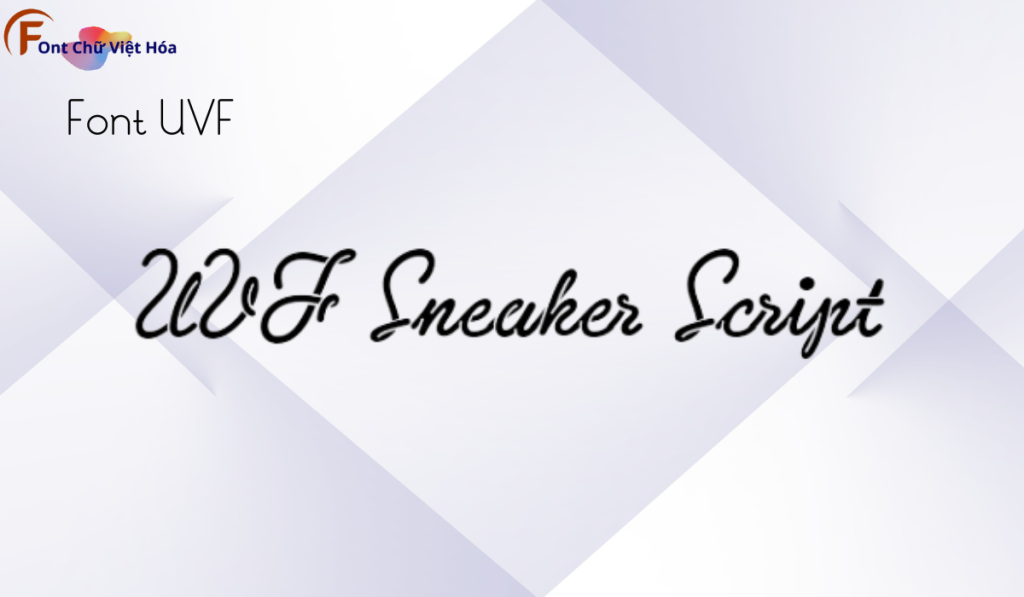
Font UVF Sneaker Script Việt Hóa
Bộ Font: UVF
Kiểu chữ: Script
UVF Sneaker Script Việt Hóa, thuộc bộ font UVF, mang phong cách chữ thảo với các đường nét mềm mại và tinh tế. Font này được thiết kế nhằm mục tiêu tạo ra sự thanh lịch và dễ đọc, đặc biệt phù hợp cho các thiết kế như thiệp mời, poster, và logo. Đặc điểm hình dạng của UVF Sneaker Script là các đường nét rõ ràng và tỷ lệ chữ cân đối, giúp tạo ấn tượng thị giác mạnh mẽ và sự thanh lịch trong từng chi tiết. Font này cũng đã được Việt hóa, mang đến sự linh hoạt và tiện dụng cho các dự án thiết kế bằng tiếng Việt, giúp người dùng dễ dàng tiếp cận và sử dụng.